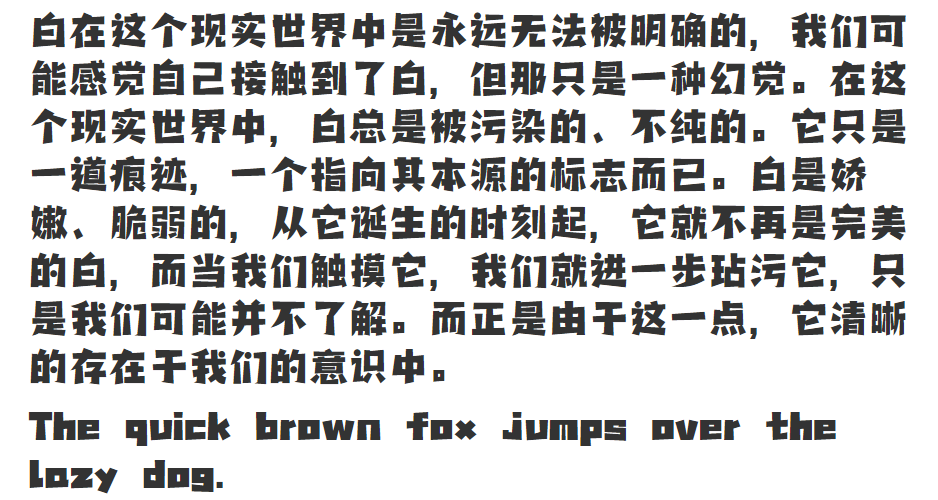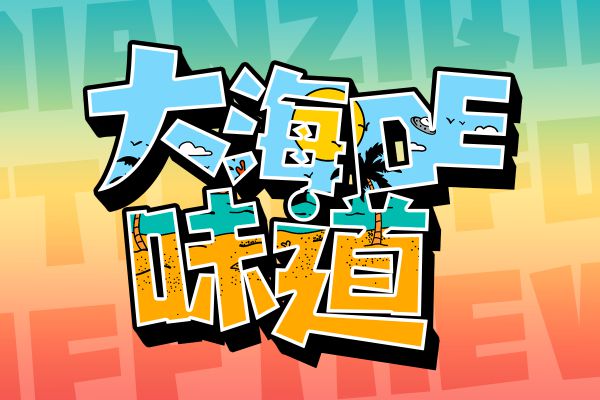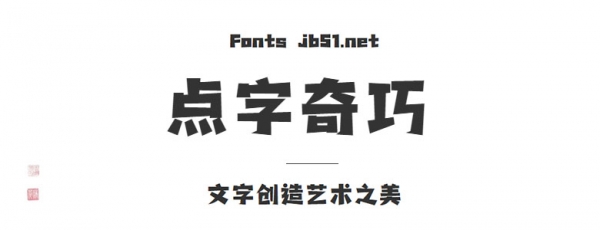
點字奇巧字體,字形結(jié)構(gòu)輕松,歡快,筆畫可愛俏皮。吸引眼球,筆畫原點設(shè)計增加了字體的輕松感;弧度的處理方式增強了字體曲線感。適用于娛樂、帶有輕松氣氛的場景,歡迎需要的伙伴前來下載使用。
風(fēng)格
溫和親切 / 有趣/卡通/創(chuàng)意字體
應(yīng)用領(lǐng)域
標(biāo)志 / 廣告 / 游戲 / 動漫 / 影視 / 包裝
字體應(yīng)用示例